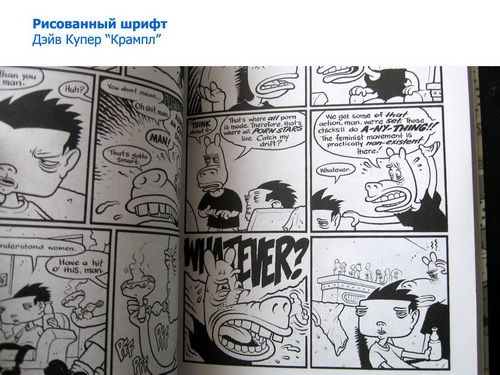
Шрифт в комиксе: наборный или рисованный Выступление 11.11.2010 по Скайпу в Московском комикс-клубе
В классических комиксах шрифт обычно рисованный. Более того, в американских мейджорских издательствах комиксов рисованем шрифта в диалогах (это называется «леттеринг») занимается отдельный человек (хотя звукоподражательные слова может рисовать и сам художник.)
Существуют определенные стандарты на рисунок такого шрифта: как правило, это рубленый шрифт (шрифт без засечек), только прописные буквы, уменьшенный интерлиньяж (межстрочное расстояние), широко употребляется выделение отдельных слов полужирным и наклонным начертанием.
Шрифт рисуется тем же инструментом, каким делается обводка (инкинг), чтобы выдержать комикс в едином стиле. Как правило, толщина штриха рисунка и толщина штриха букв совпадают, это дает ощущение одного масштаба деталей на странице.
Однако, если делать аккуратные рукописные надписи в комиксе, это довольно долго, требует особой подготовки, а в случае ошибки, сложно исправляется (ошибки заклеивается или замазывается белилами и перерисовываются).
Сейчас, в эру повсеместного применения компьютерных технологий, в нынешних иностранных комиксах, как правило, используются цифровые наборные шрифты.
Плюсы наборного шрифта неоспоримы: скорость, аккуратность, возможность правки, бесконечное (в рамках удобочитаемости, конечно) количество вариаций кегля, интерлиньяжа, ширины букв, межбуквенного расстояния, отступов, декоративных эффектов.
Минусы: монотонность набора, одинаковый рисунок букв, а главное: жестко заданный стиль шрифта, который может совсем не совпадать со стилем графики, невозможность исправить его пропорции, толщину штриха, величину выносных элементов и пр., отсутствие спонтанности в его рисунке, сниженная эмоциональность. Выражаясь образно, наборный шрифт «неживой».